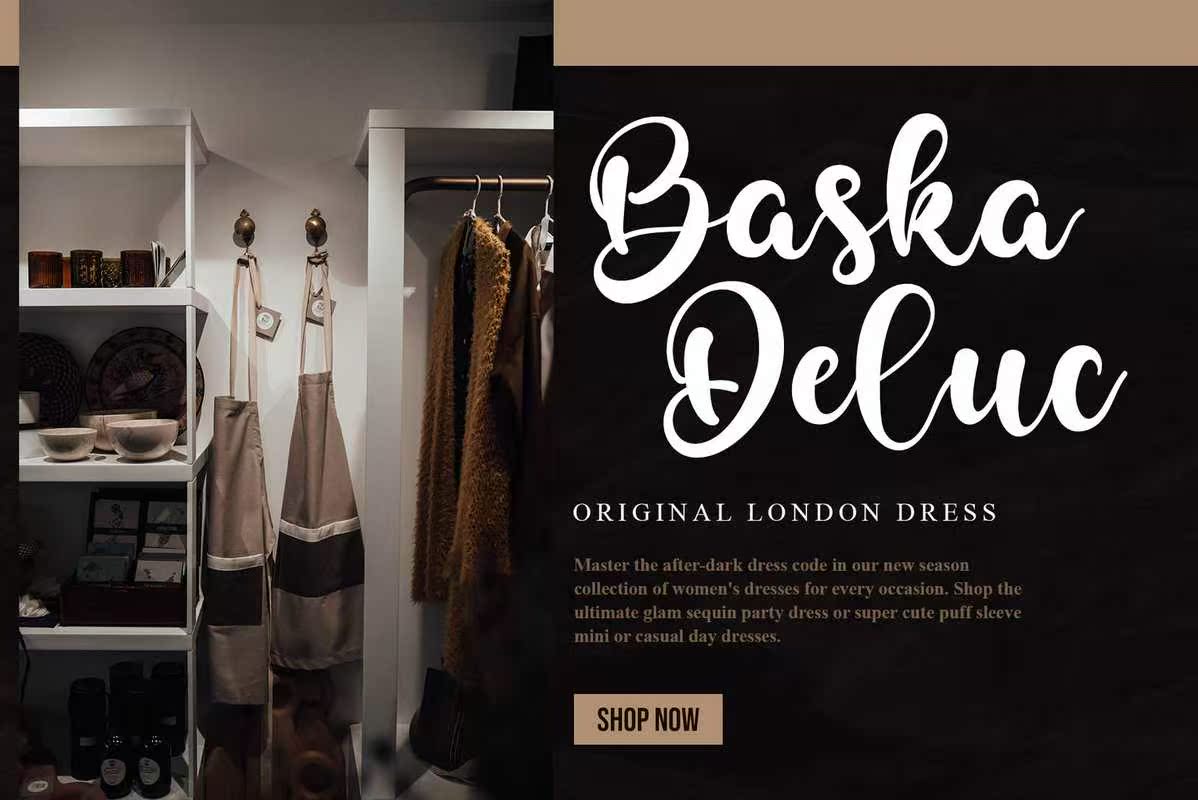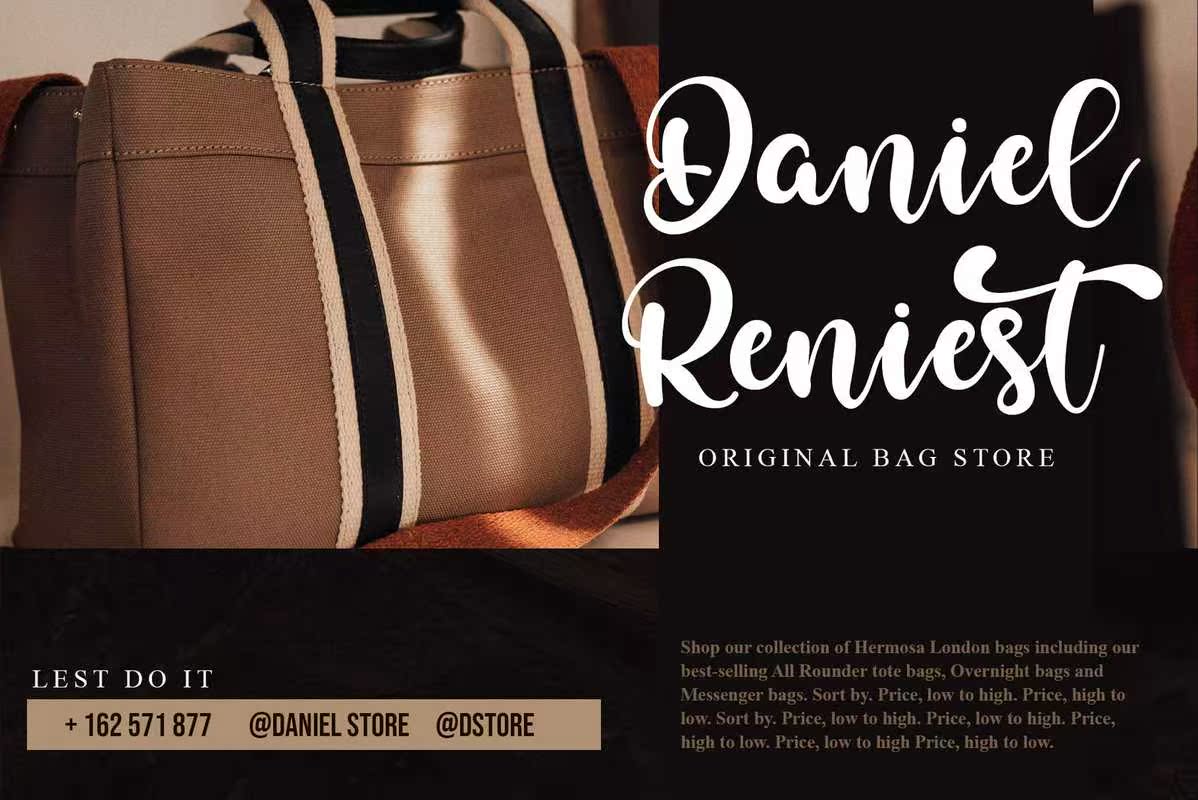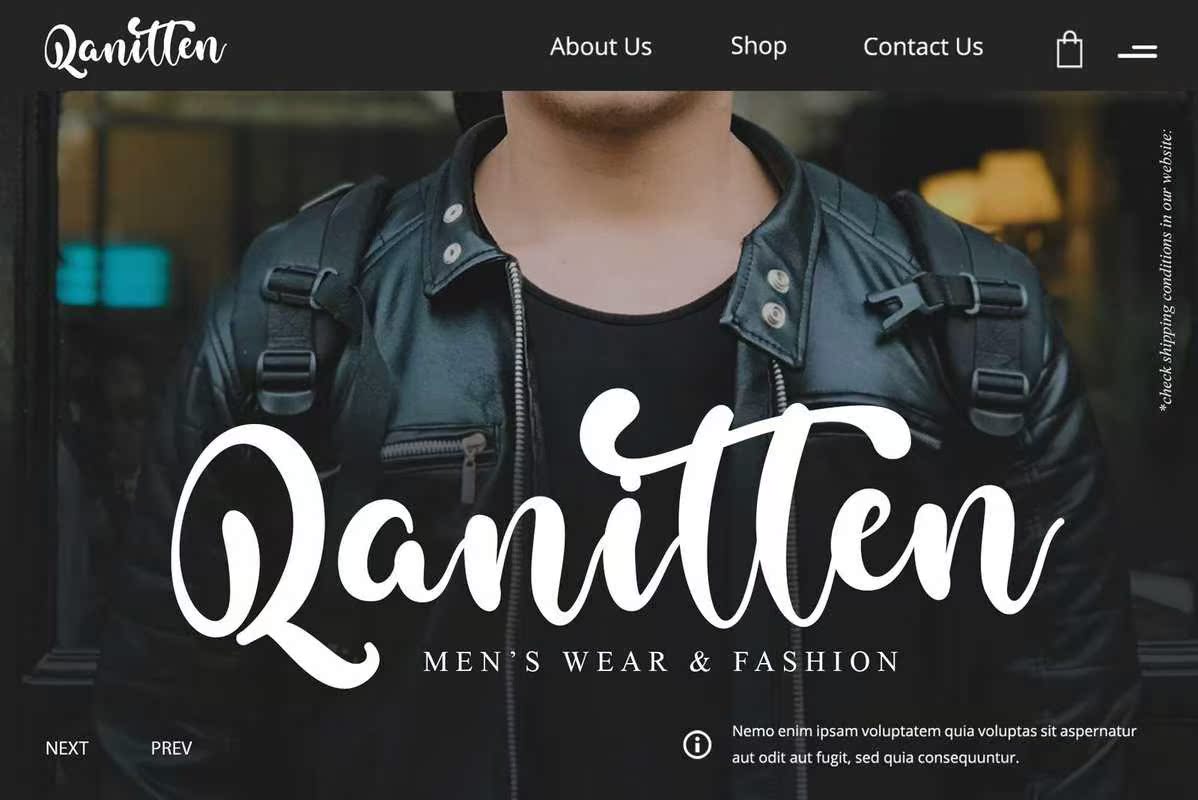
BaileyAustinALuxurySignatureTypeFont,一个适合您项目的文字和数字集合,非常适合于标识、品牌设计、标志设计、数字刻字艺术、T恤/服装、海报、杂志、标志、广告设计,任何设计都需要BaileyAustinALuxurySignatureTypeFont,一个适合您项目的文字和数字集合,非常适合于标识,品牌设计、标志设计、数字文字艺术、T恤/服装、海报、杂志、标志、广告设计和任何设计需求